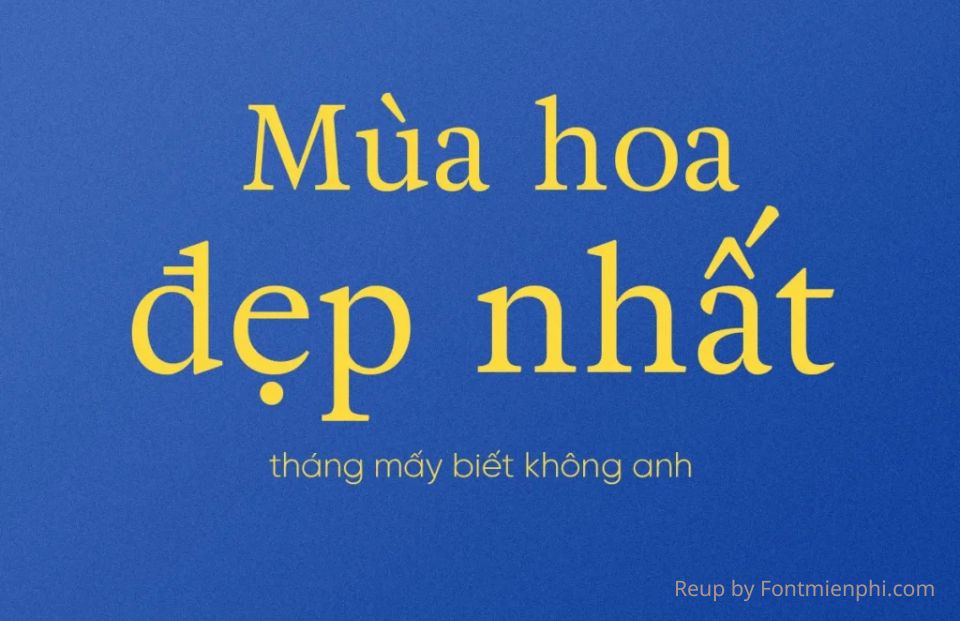
Font VL Adriane Text Việt Hóa Miễn Phí
Giới Thiệu: Font VL Adriane Text Việt Hóa Miễn Phí
Đúng như tên gọi, Adriane Text là kiểu phông chữ có chân (serif) được thiết kế đặc biệt và tối ưu hóa tối đa cho các nội dung văn bản dài như sách, truyện chữ, báo chí và tạp chí. Nếu từng yêu thích sự mềm mại của phiên bản VL Adriane Swash, bạn sẽ nhận thấy Adriane Text mang một diện mạo hoàn toàn khác: mạnh mẽ hơn, cứng cáp và cực kỳ sắc nét. Sự thay đổi này mang lại một cảm giác vô cùng hiện đại, dứt khoát và chuyên nghiệp khi áp dụng vào dàn trang.
Hơn thế nữa, phiên bản đang được phát hành miễn phí trên Fontmienphi.com đã được Việt hoá trọn vẹn. Hệ thống dấu tiếng Việt được tinh chỉnh kỹ lưỡng giúp văn bản hiển thị mượt mà, đồng bộ và đạt chất lượng sắc nét nhất trên cả ấn phẩm in ấn lẫn các nền tảng kỹ thuật số.
🌟 Đặc Điểm Nổi Bật Của Font VL Adriane Text
• Sức mạnh của Serif: Thiết kế nét chữ có chân mạnh mẽ, rõ nét, tạo độ vững chãi cho tổng thể trang giấy hoặc màn hình.
• Trải nghiệm đọc hoàn hảo: Cấu trúc chữ được tính toán tỉ mỉ để tối ưu khả năng đọc, giúp mắt người xem luôn thoải mái khi tiếp thu những đoạn văn bản dài.
• Sự khác biệt rõ rệt: Nét chữ cứng cáp, hiện đại và dứt khoát hơn hẳn so với người anh em VL Adriane Swash.
• Thuần Việt 100%: Hỗ trợ đầy đủ bộ mã ký tự và dấu tiếng Việt chuẩn xác.
• Đa nền tảng: Hiển thị xuất sắc, giữ nguyên độ chi tiết và sắc nét dù bạn sử dụng để in ấn thực tế hay hiển thị trên các thiết bị điện tử.
🎨 Ứng Dụng Thực Tế
Với sự chuyên nghiệp và tính ứng dụng cao, VL Adriane Text tại Fontmienphi.com là sự lựa chọn không thể bỏ qua cho các hạng mục:
• Dàn trang các tác phẩm sách, tiểu thuyết và truyện chữ nhiều tập.
• Thiết kế layout, trình bày nội dung cho các trang báo, tạp chí.
• Phát triển các nội dung editorial (biên tập) đòi hỏi sự chuyên nghiệp và tính học thuật cao.
• In ấn tài liệu văn phòng, báo cáo dài kỳ cần sự chỉn chu.
• Sáng tạo các tác phẩm typography serif mang hơi hướng hiện đại, thanh lịch.
• Xây dựng giao diện cho các trang blog và website thiên về chia sẻ nội dung, kiến thức.